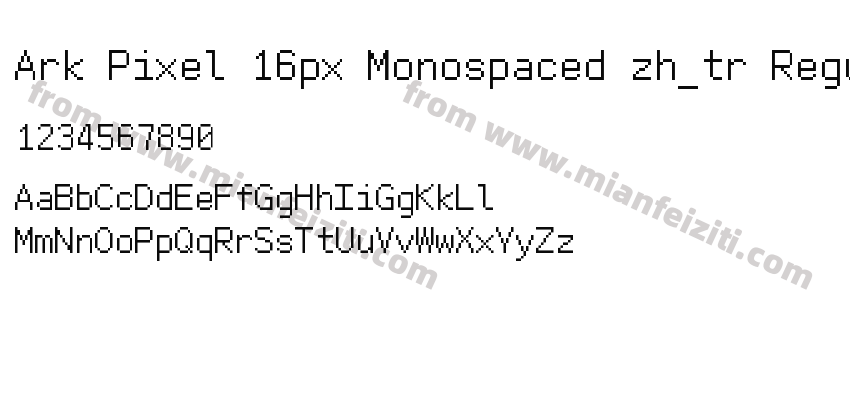
Ark Pixel 16px Monospaced zh_tr Regular
字体名称: Ark Pixel 16px Monospaced zh_tr Regular
Postscript名称: Ark-Pixel-16px-Monospaced-zh_tr-Regular
字体版本: 2024.11.04
本款“Ark Pixel 16px Monospaced zh_tr Regular”是一款书写很新颖的字体,字体大方,适合各种设计作品使用!欢迎下载!